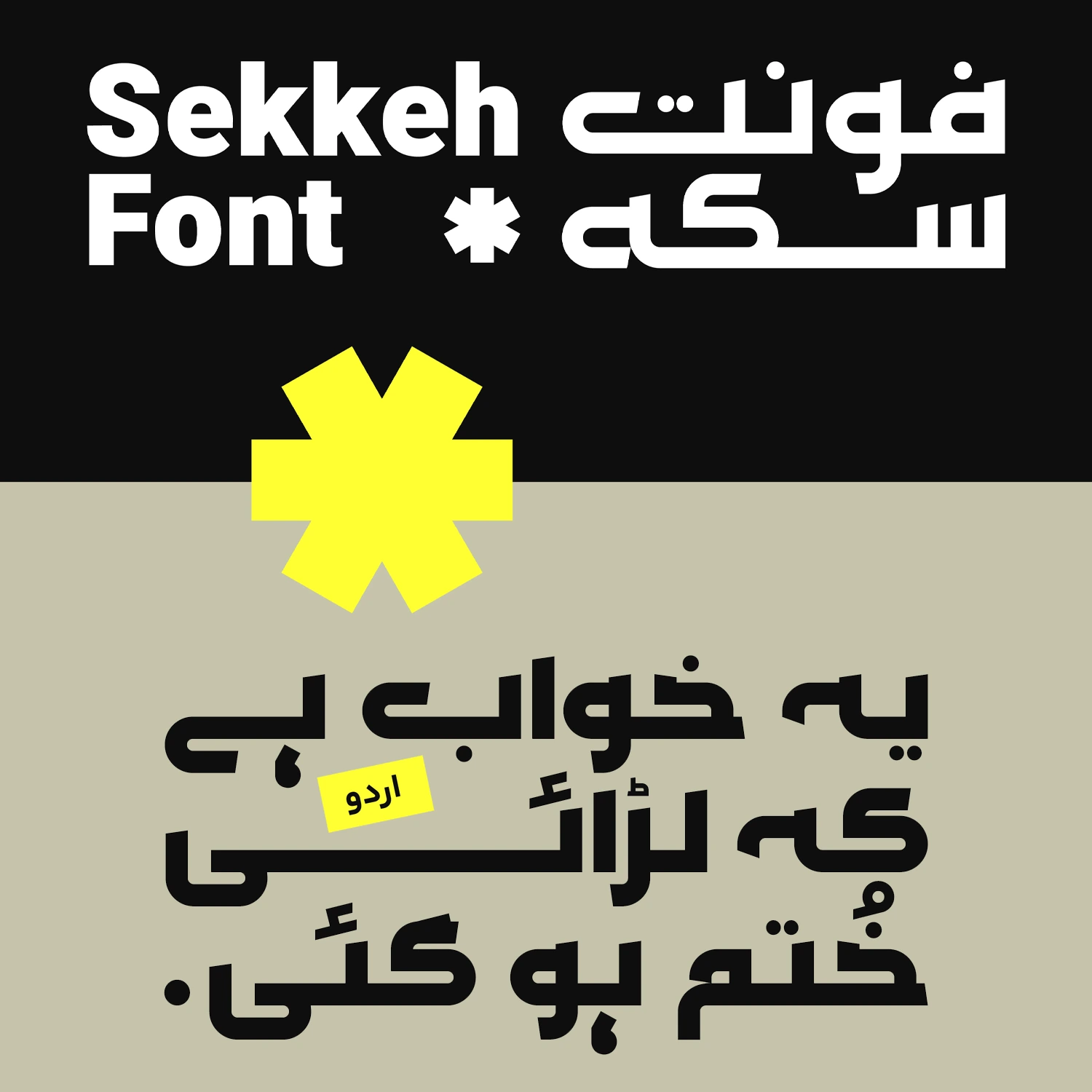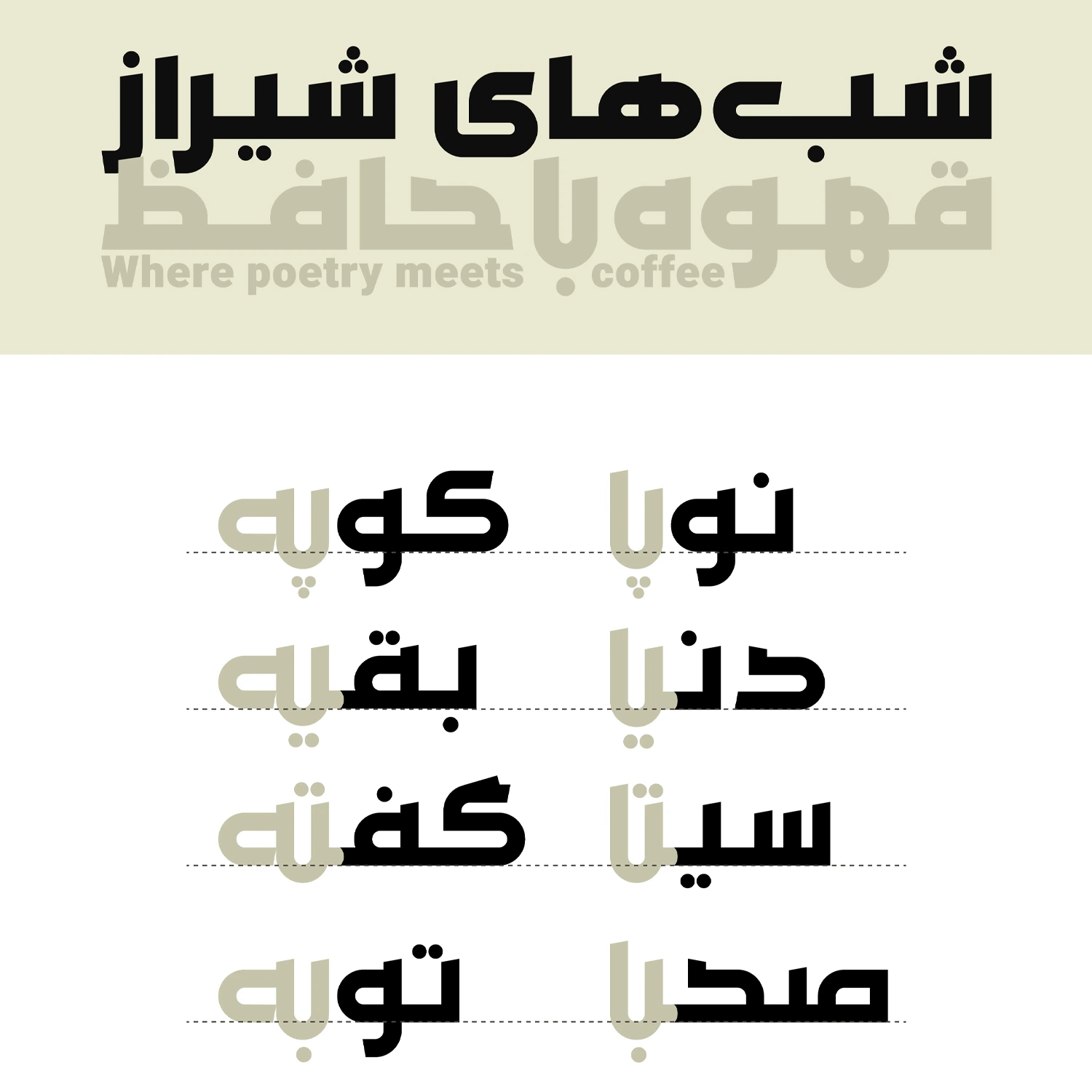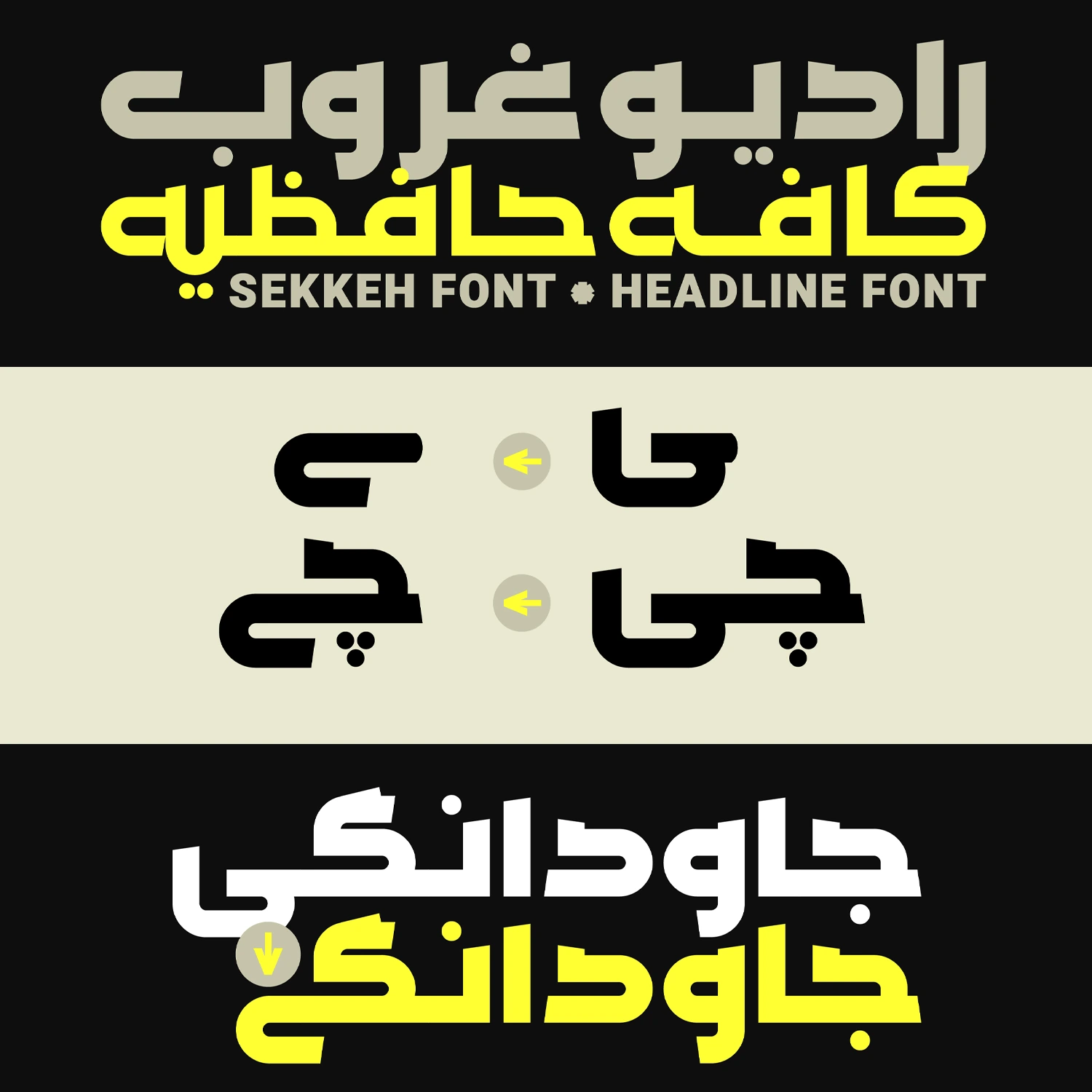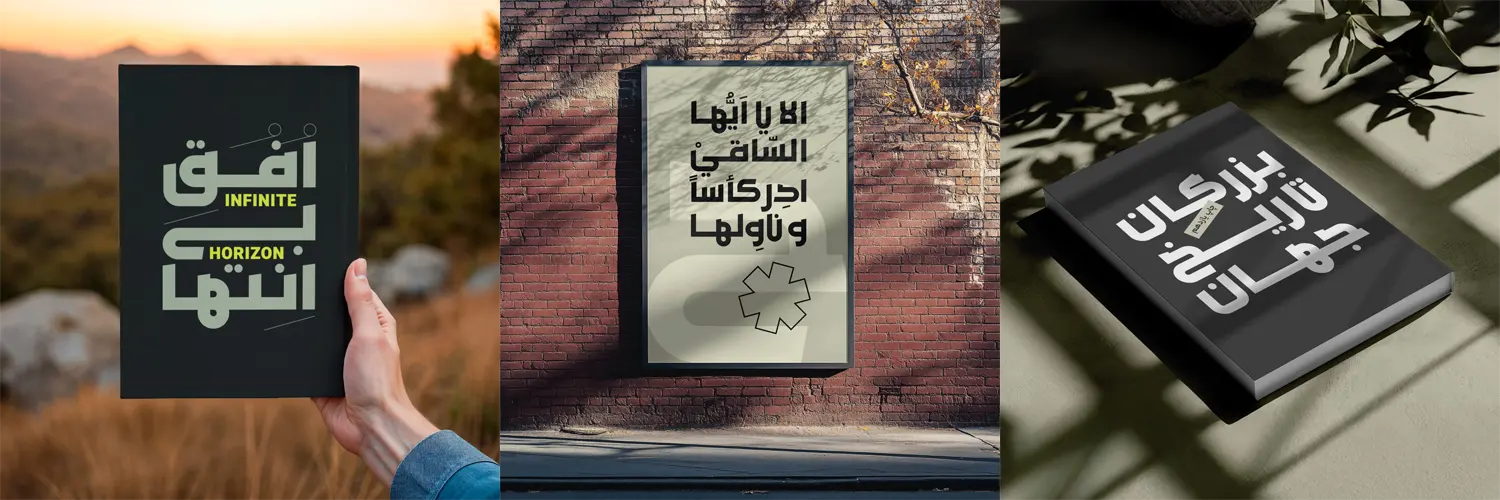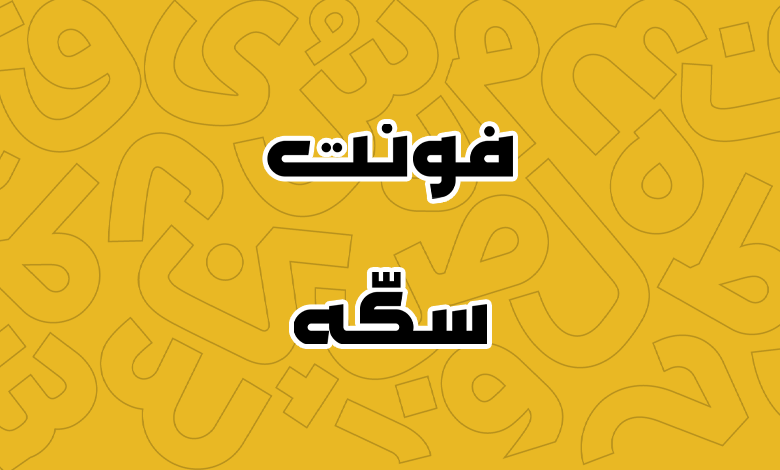
فونت سکه (Sekkeh)
فونت سکه (به انگلیسی: Sekkeh) با نگاهی پژوهشی و تاریخی به سکههای ایرانی شکل گرفته است و در تلاش است تا هویت و تاریخ کشورمان ایران را که زمانی بر روی سکهها نمود داشتند، به دنیای حروف وارد کند. این فونت از دو وزن سیاه و چاق پشتیبانی میکند که میتوانید برای متون کوتاه از آن استفاده کنید.
فونت سکه حس اصالت، صلابت و هویت نوشتاری گذشته را در بستر دنیای مدرن امروزی بازآفرینی میکند. این فونت که دارای ساختاری هندسی و بر اساس تناسبات ریاضی است توسط فاطمه چراغی طراحی شده و توسعه نرمافزاری آن را شهرزاد اکبری انجام داده است.
در طراحی فونت فارسی سکه ترکیبی از زوایای تند با انحنای کنترل شده استفاده شده است. چنین ساختاری را معمولا در خطوط کوفی میبینیم که هم لطافت بصری را از خود نشان میدهند و هم در عینحال ساختاری قدرتمند و جدی را از خود نشان میدهند که با خطوط مستقیم ترسیم میشود.
فرمهای دایرهای الهامگرفته از قالب سکه و برشهای منظم خطوط، باعث شدهاند که این فونت نظم، تعادل و هارمونی قابلتوجهی داشته باشد.
هندسه دقیقی که در طراحی این فونت پیادهسازی شده، ساختار حروف را بر پایهی مربع، دایره و خطوط مستقیم استوار ساخته که در نتیجه، فرمها از هماهنگی چشمنوازی برخوردارند. ضخامت و فضاها در چشمیها نیز بهگونهای تنظیم شدهاند که حتی در وزنهای سنگین نیز خوانایی خوبی دارند.
فونت سکه از نظر بصری، میان سنت و مدرنیته حرکت میکند. در نگاه اول، با حالوهوای تاریخیاش یادآور سنگنوشتهها و خطوط کوفی دارد، اما در بطن خود ساختاری کاملا معاصر و مینیمال را پنهان کرده است. این دوگانگی باعث میشود سکه در پروژههای فرهنگی، هنری و تبلیغاتی بسیار جذاب عمل کند؛ چون نه بیش از حد کلاسیک است که بهروز بودنش زیر سؤال برود، و نه آنقدر مدرن که ارتباط خود را با ریشههای بصری فارسی از دست بدهد.
انتهای حروف با زاویهها و برشهای یکسان خاتمه مییابند تا شخصیت گرافیکی فونت پایدار و حرفهای بهنظر برسد. در پایان نیز برخی ترکیبات و حروف این فونت دارای ساختار Alternative با طراحی اختصاصی هستند تا این فونت را که برای استفاده در عناوین مناسب است، بیش از پیش نمایشیتر کنند.
فونت سکه پلی میان فرهنگها
فونت فارسی سکه محدود به این زبان نیست و همانطور که سکههای قدیمی ارتباطی میان اقوام و ملل مختلف داشتند، در این فونت نیز ارتباط با فرهنگهای مختلف حفظ شده است. عربی، اردو، کردی و اردو از دیگر زبانهای پشتیبانی شده در این فونت هستند. هر زبان ساختار کاملا استاندارد خود را دارد.
در زبانهای عربی و اردو که شاهد استفاده از اعراب و گلیفهای تزئینی با برخی تغییرات در حروف و اعدادی مانند «۰۴۵۶» هستیم، سکه این تفاوتها را بهخوبی رعایت کرده است. برای زبان انگلیسی نیز همین ساختاری وزنی و پیچش حروف رعایت شده است که سکه را به قلمی بینالمللی تبدیل میکند.
ساختاری نمایشی و مناسب عناوین
همانطور که اشاره شد این فونت برای استفاده در متون بلند مناسب نیست. اگر هم صحبتی از متون بلند باشد، بهتر است در ابعاد بزرگی مانند چاپ بنر و بیلبورد باشد که جنبه اطلاعرسانی و خبر را دارد. اما در مقابل این فونت برای عناوین و متون کوتاهی که جنبه شعاری، تبلیغاتی یا طراحی گرافیکی همچون پوستر دارند خود را به خوبی نمایان میکند.
یکی از نقاط قوت این فونت استفاده از لیگچرها و ترکیبات خاص است که برخی از حروف ساختاری نمایشیتر میگیرند تا بیشتر جلب توجه کنند. ترکیباتی مانند «لا، ی، م، ـه، ـا» در این فونت بسته به حروف قبلی یا بعدی خود شکل متفاوتی به خود میگیرند تا ساختار فونت نمایشیتر شود.
از طرفی دیگر در طراحی چشمی حروف و منحنیها از ترکیبات دایرهای و متسطیل استفاده شده است که ساختار وجود سکه درون آنها را نشان میدهد. هماهنگی چشمیها با زوایای مستقیم و منحنیهای بیرونی خطوط، این فونت را بیش از پیش زیباتر کرده است.
با چنین ویژگیهایی میتوان از این فونت در کاربردهای مختلفی استفاده کرد:
- تیتر و عنوانهای بزرگ در پوسترها
- جلد کتاب و مجلات فرهنگی با موضوعات تاریخی
- لوگوتایپ و برندهای هنری، مد و پوشاک
- طراحی بستهبندی محصولات
- طراحی گرافیک شهری در بیلبوردها و بنرها
- پست و تامنیل شبکههای اجتماعی
ریتم منظم این فونت، باعث میشود عناوین ساختاری قاطعانه و ماندگار از خود نشان دهند. بهویژه در ابعاد بزرگ که با هدف تبلیغات یا شعار مورد استفاده قرار گرفته باشند.